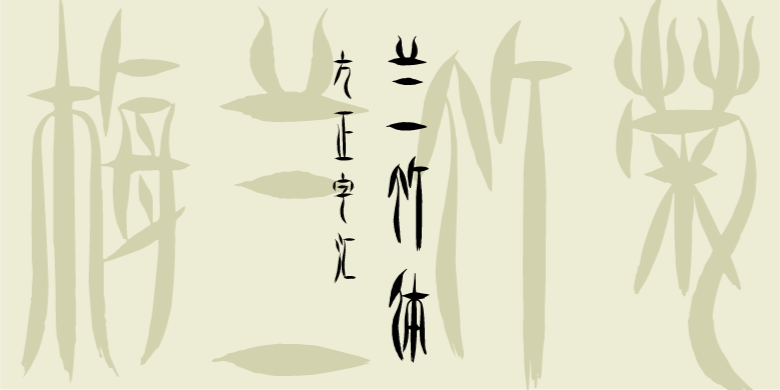
方正字迹-兰竹体
兰竹体是在继承传统书法的基础上,体现了现代书法创新的四大特征:一、兰竹体是真正意义上字画融为一体的书法;二、兰竹体是充分体现了儒、释、道三学素养的书法;三、兰竹体能够形象的表现出作者所要表达的心境,外意于形,内修于禅;四、兰竹体有效的将人与自然融为一体,是书韵、画韵、气韵相聚合的书法艺术。
兰竹体又称君子体,是艺术家张迎先生历经几十年对中国传统书体的研习和探索之后而创造出来的。其借鉴二千余年前楚简中的柳叶笔法,进而借用四君子兰、竹之叶作为汉字的笔画线条,字形上借鉴大篆、小篆,融贯汉隶,参酌章草,吸取飞白,从而形成了一种新的书法艺术形式。
兰竹体诞生在漕运第一码头——北京通州张家湾古镇,是中华传统文化古为今用的典范;是大运河文化的一部分;是京城文脉的代表之一。兰竹体有理可依——«论兰竹体»论文,有典可查——«兰竹体书法大字典»,有帖可临——«兰竹体字帖»,已经形成了完整的书法书体体系。